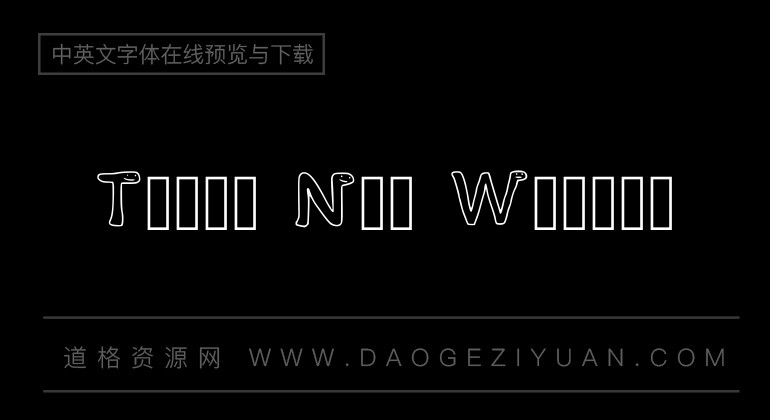
Times New Wumpus
很抱歉,Times New Wumpus 字体并不是一种真正存在的字体。它似乎是基于《勇士游戏》(Hunt the Wumpus)这个早期计算机游戏的笑话,将游戏中的 Wumpus 角色与 Times New Roman 字体的名称混合在一起而得来的。所以,如果你在任何字体库中搜索 Times New Wumpus 字体,你不会找到它。
Times New Wumpus是一款非常不错的手写艺术字体,具有很好的视觉感,适合于文化类的宣传设计、商业类品牌的广告和产品包装设计以及个性化文字排版等较多场景。